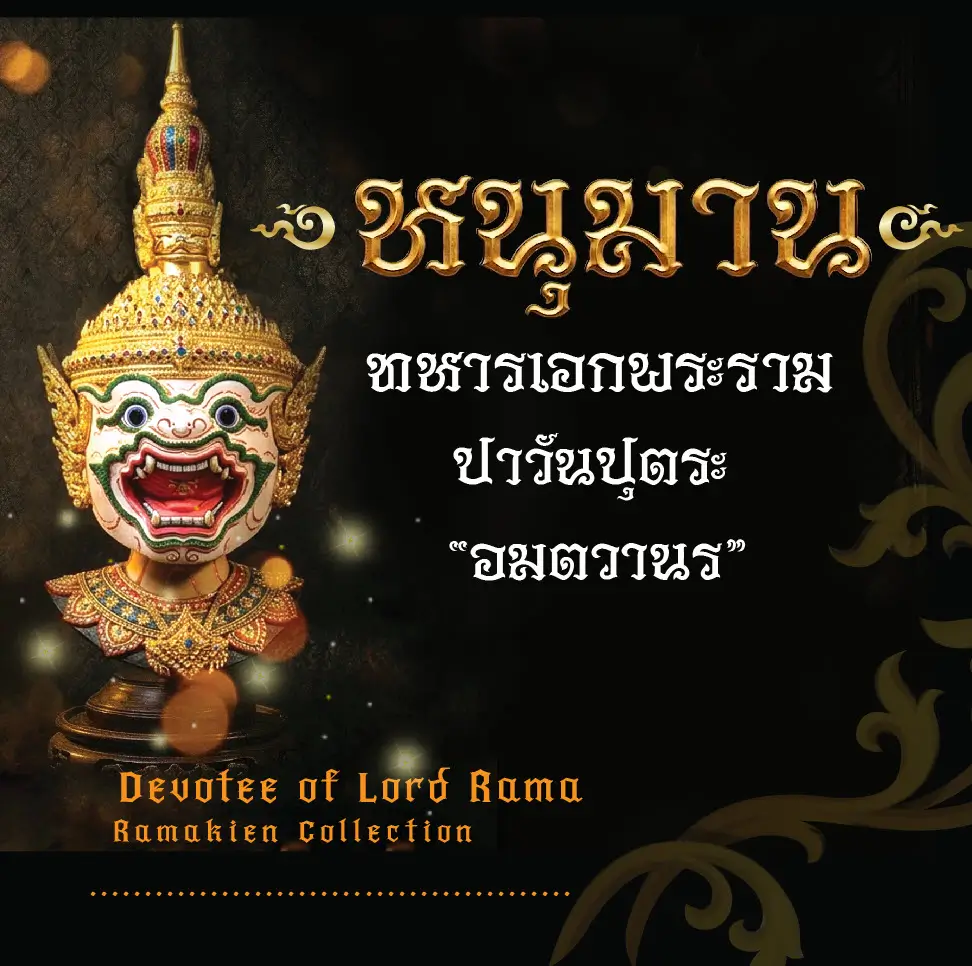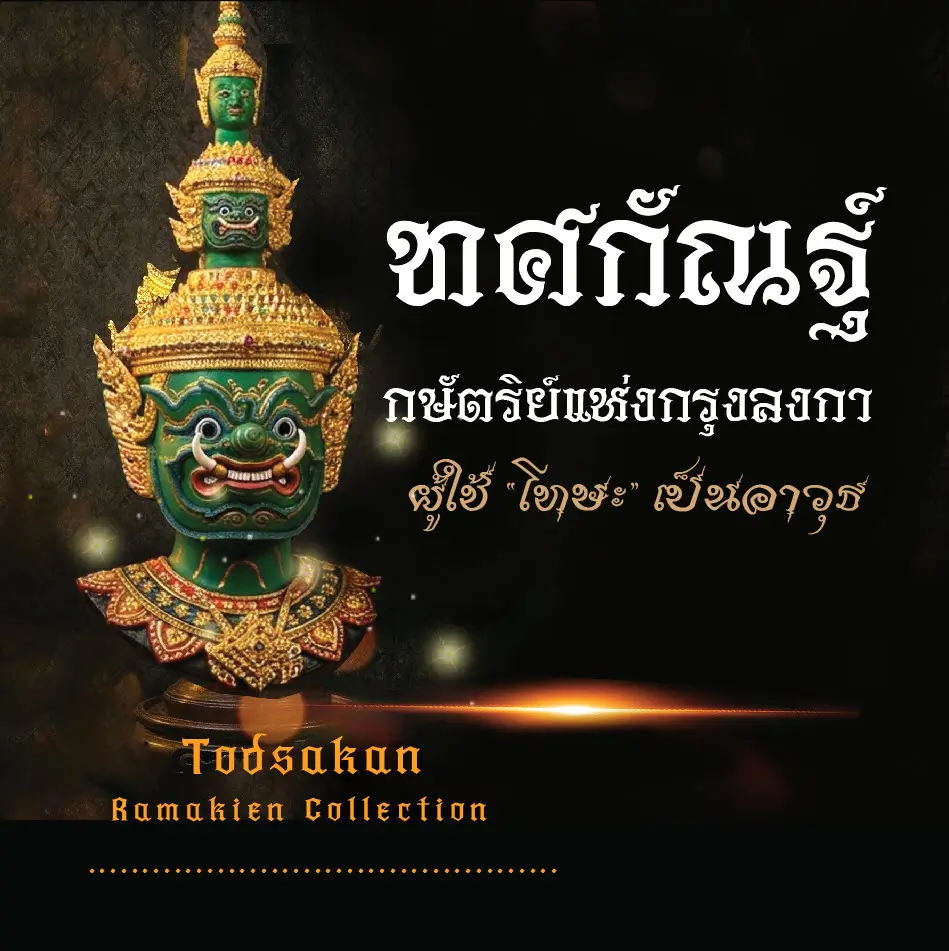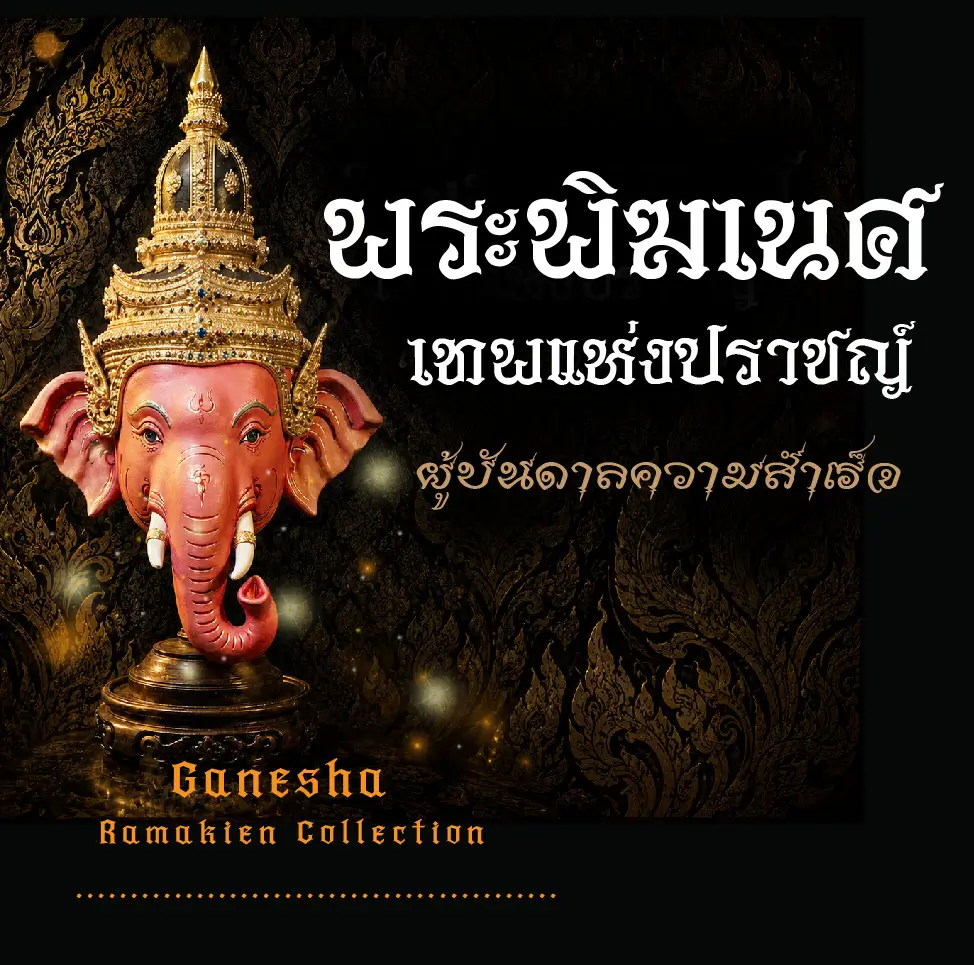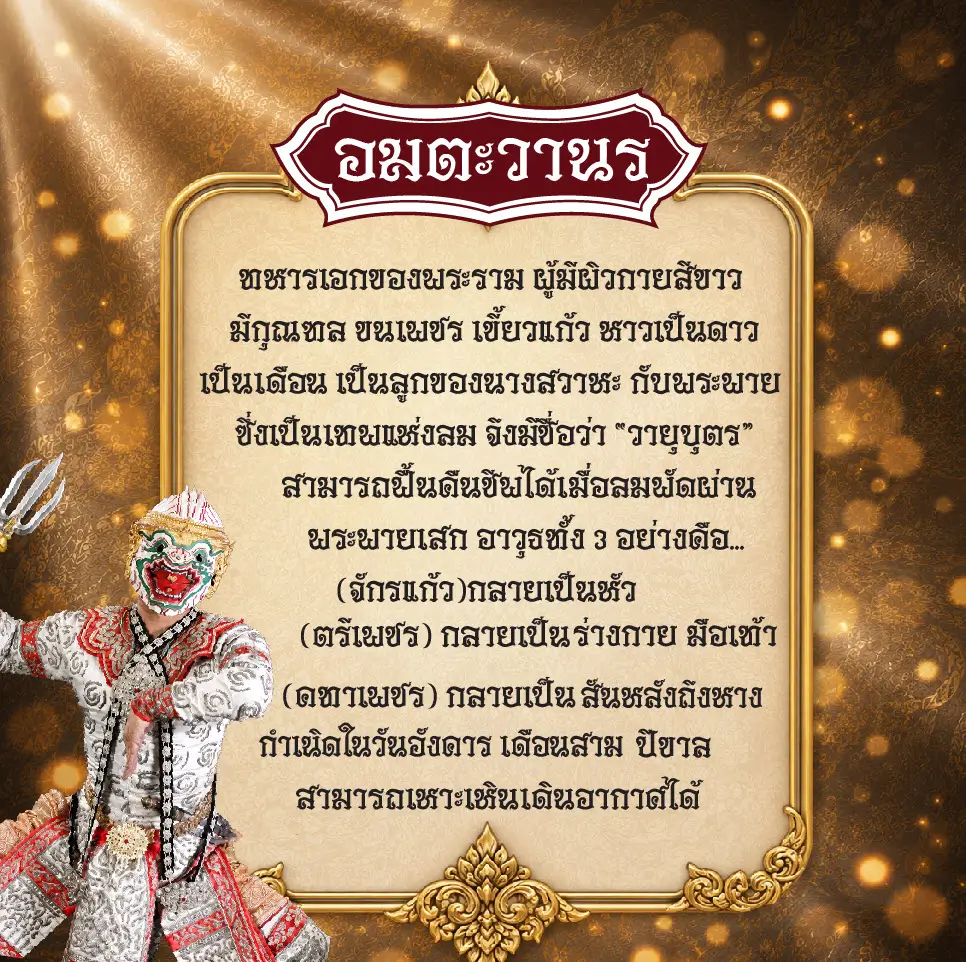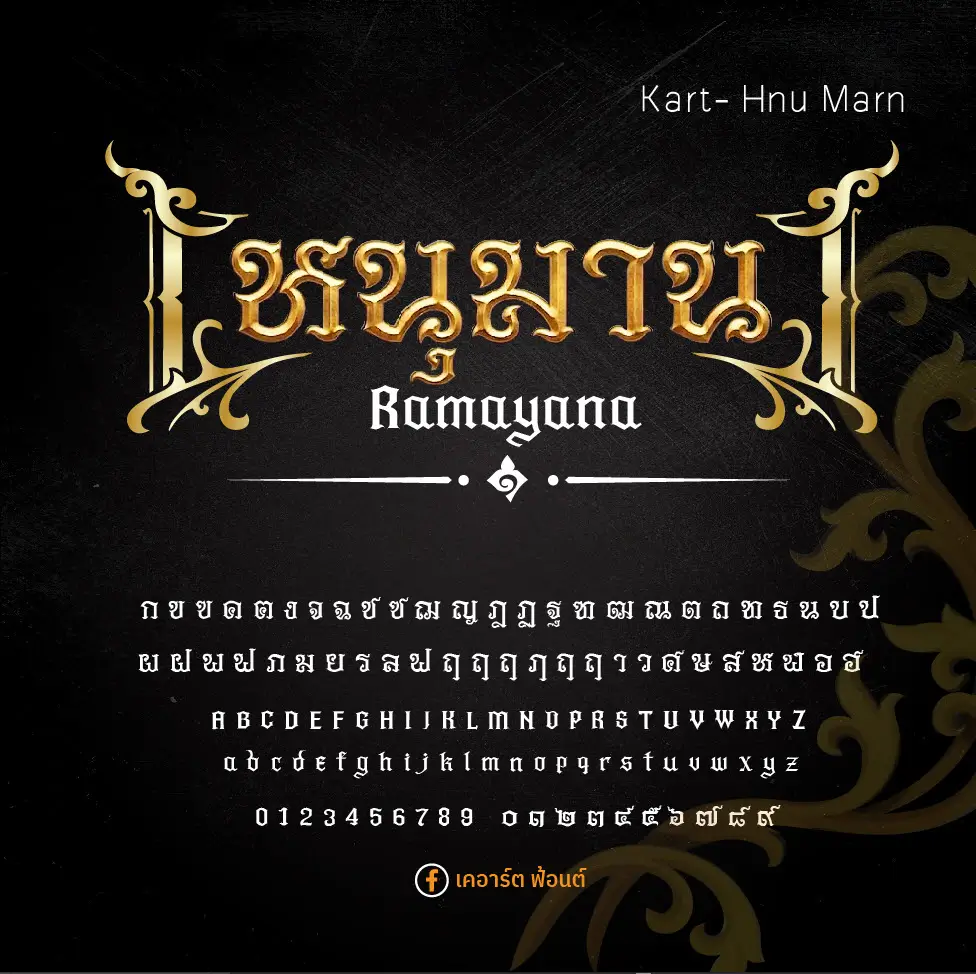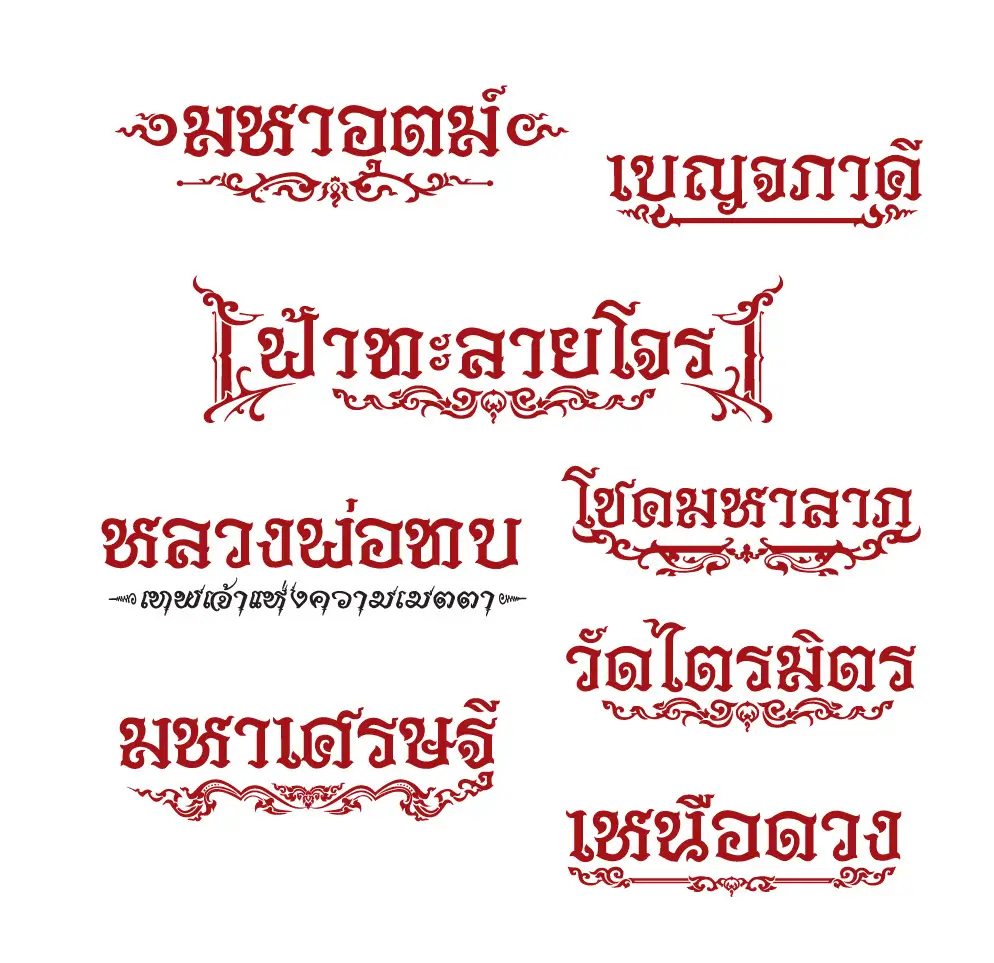
ฟอนต์ เคอาร์ต-หนุมาน (Kart- Hnu Marn) – เป็นฟอนต์ที่เขียนเน้นใช้งานแนว #ฟอนต์ไทย #ฟอนต์ลายไทย #ฟอนต์พระเครื่อง #ฟอนต์แนวไทย #อักษรวิจิตร #ฟอนต์พุทธศิลป์ ฟอนต์มีลายกนกในฟอนต์ ครับ
เคอาร์ต หนุมาน (Kart-Hnu Marn)